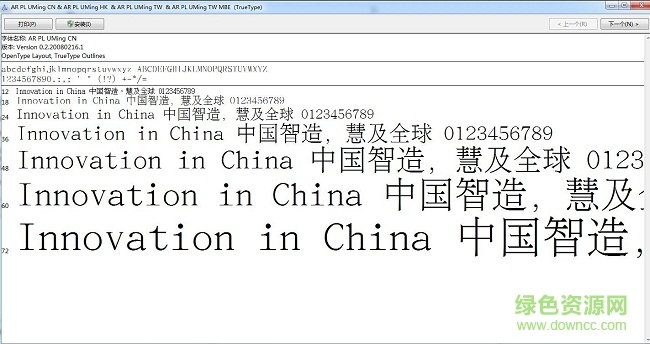
ar pl uming cn字體
ar pl uming cn是什么字體?ar pl uming字體是linux操作系統(tǒng)的預(yù)裝字體,線條纖細(xì),筆畫簡潔,整體給人的感覺就是干凈優(yōu)雅,用在書刊和網(wǎng)頁設(shè)計(jì)中效果十分融洽,有需要這款字體的朋友歡迎免費(fèi)下載!